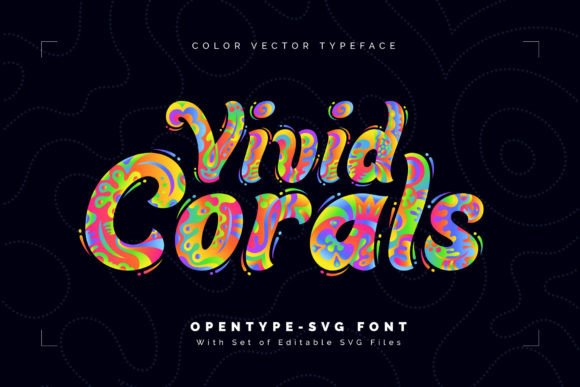
Vivid Corals Font
Vivid Corals Font – خط إبداعي مستوحى من ألوان الشعاب المرجانية
امنح تصاميمك لمسة فريدة مع Vivid Corals Font، خط أنيق ومبتكر مستوحى من الألوان الزاهية والتفاصيل المميزة لعالم الشعاب المرجانية. يتميز هذا الخط بأسلوب عصري يجمع بين الانسيابية والوضوح، مما يجعله مثاليًا لمجموعة واسعة من الاستخدامات، مثل الشعارات، والتصاميم الإعلانية، والبطاقات، وتصميم المنتجات الرقمية.
✔ تصميم فريد يعكس الإبداع والتميز
✔ مثالي للعلامات التجارية، والمجلات، والمواقع الإلكترونية
أضف لمسة من الجمال والحيوية إلى مشاريعك مع Vivid Corals Font! ????